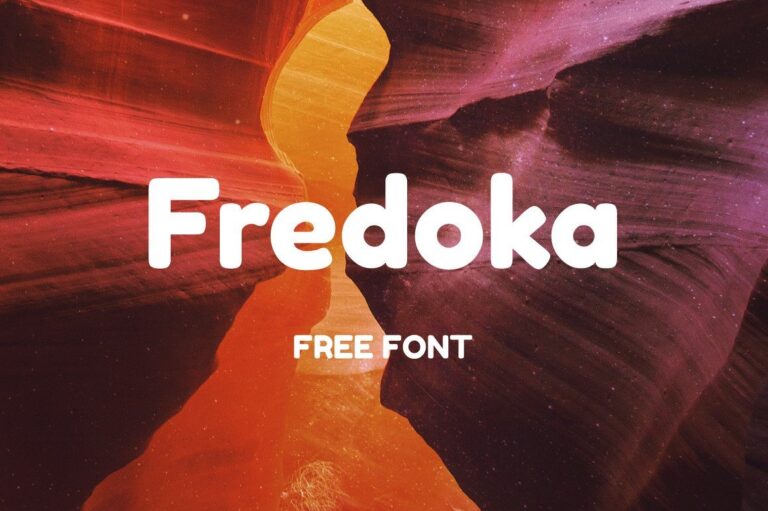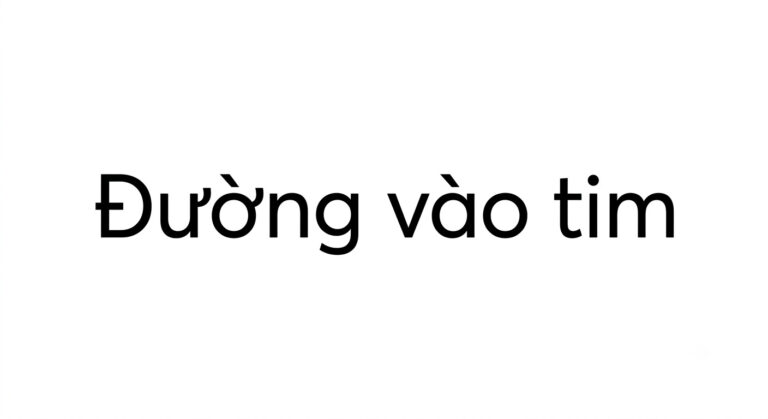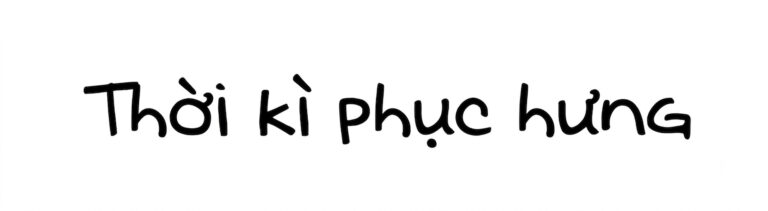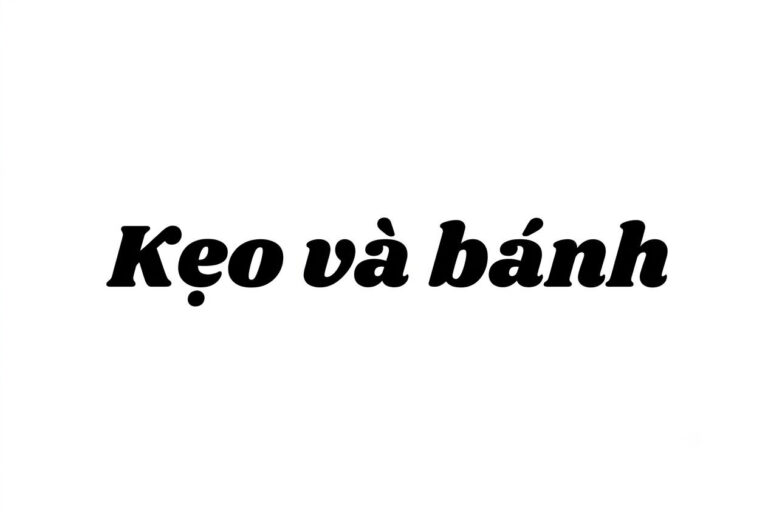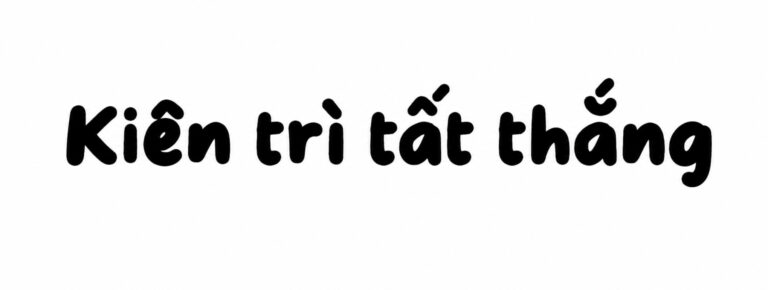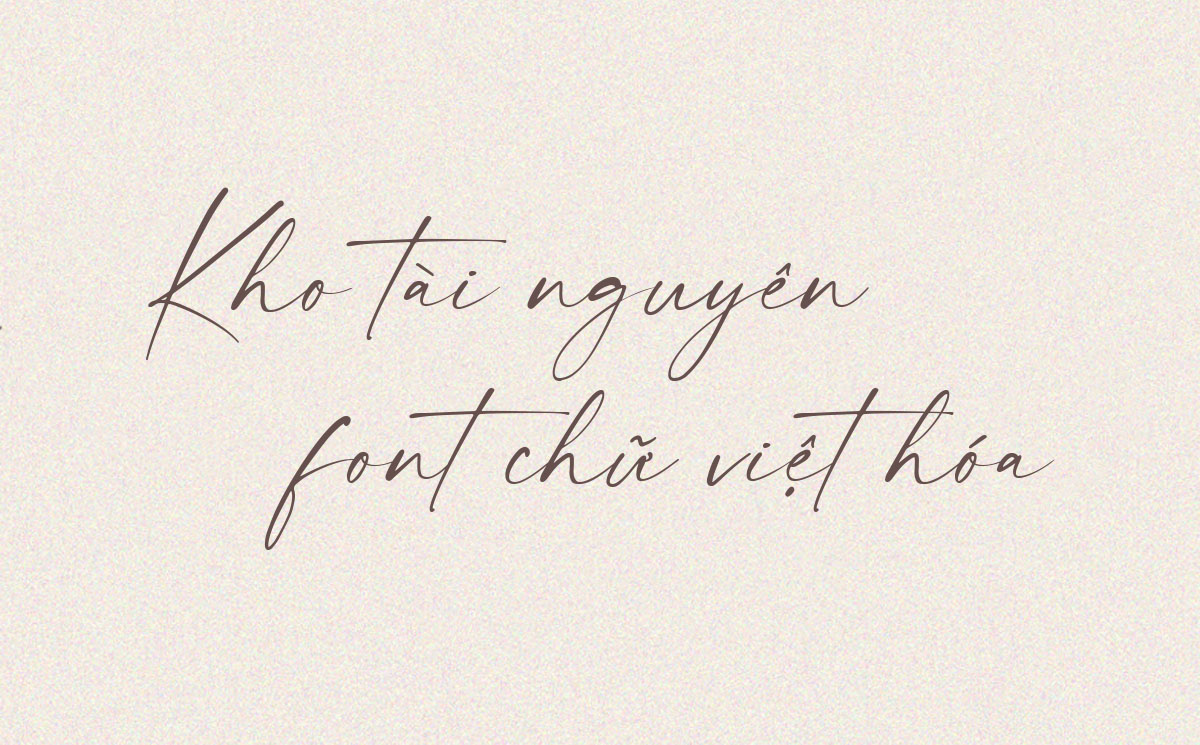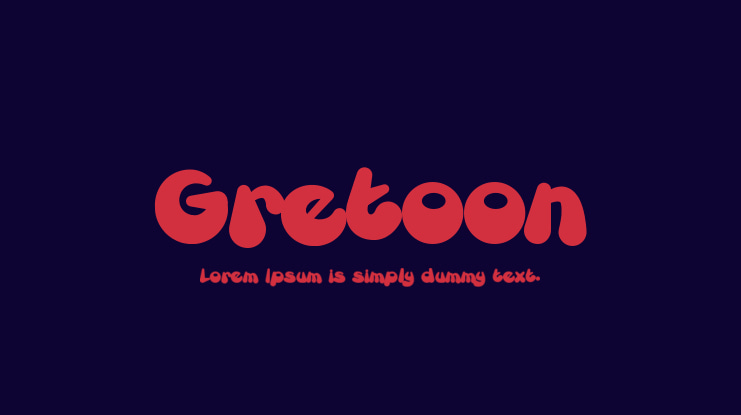
Tải 10+ bộ Font Handwriting Việt hóa sắc nét chuyên cho thiết kế bao bì
Nhiều designer gặp khó khăn khi tìm kiếm Font Handwriting Việt hóa do một số bộ font chưa được xử lý đầy đủ ký tự tiếng Việt, dẫn đến lỗi mất dấu, sai ký tự hoặc nét chữ bị răng cưa khi đưa vào sản xuất. Những vấn đề này khiến các mẫu bao bì thủ công mất đi vẻ tự nhiên, giảm cảm giác gần gũi và tính cá nhân hóa của thương hiệu.
Xưởng In Viva cung cấp Font Handwriting Việt hóa với hệ thống ký tự chuẩn nét, hỗ trợ hiệu quả trong quá trình thiết kế logo, bao bì giấy và sản xuất các dòng quà tặng doanh nghiệp theo phong cách thủ công, sáng tạo.
Handwriting font chữ viết tay là gì?
Handwriting font chữ viết tay là tập hợp những phông chữ được thiết kế mô phỏng lại các đường nét viết tay thực tế của con người. Thay vì tuân theo những tỷ lệ hình học cứng nhắc như dòng chữ Sans-serif hay Serif, phông chữ Handwriting mang đặc trưng của sự tự do, phóng khoáng và đôi khi là sự không đồng đều có chủ ý. Tùy thuộc vào công cụ mô phỏng (bút chì, bút mực, cọ lông hay phấn), dòng phông chữ này có thể mang lại những sắc thái cảm xúc khác nhau: từ lãng mạn, nhẹ nhàng đến cá tính, bụi bặm.
Trong ngành thiết kế đồ họa và bao bì, phông chữ viết tay đóng vai trò như một cầu nối cảm xúc, giúp sản phẩm trở nên thân thiện và mang đậm dấu ấn cá nhân hơn. Tuy nhiên, bản gốc của các phông chữ này thường là tiếng Anh, khi áp dụng vào ngôn ngữ có nhiều dấu thanh như tiếng Việt rất dễ xảy ra tình trạng lỗi font, sai khoảng cách hoặc các dấu bị đè lên nhau. Bộ Font Handwriting Việt hóa do In Viva tổng hợp đã được căn chỉnh kỹ thuật tỉ mỉ, giúp các dấu tiếng Việt hòa hợp tự nhiên với nét bút gốc, mang lại sự thuận tiện cho người sử dụng.
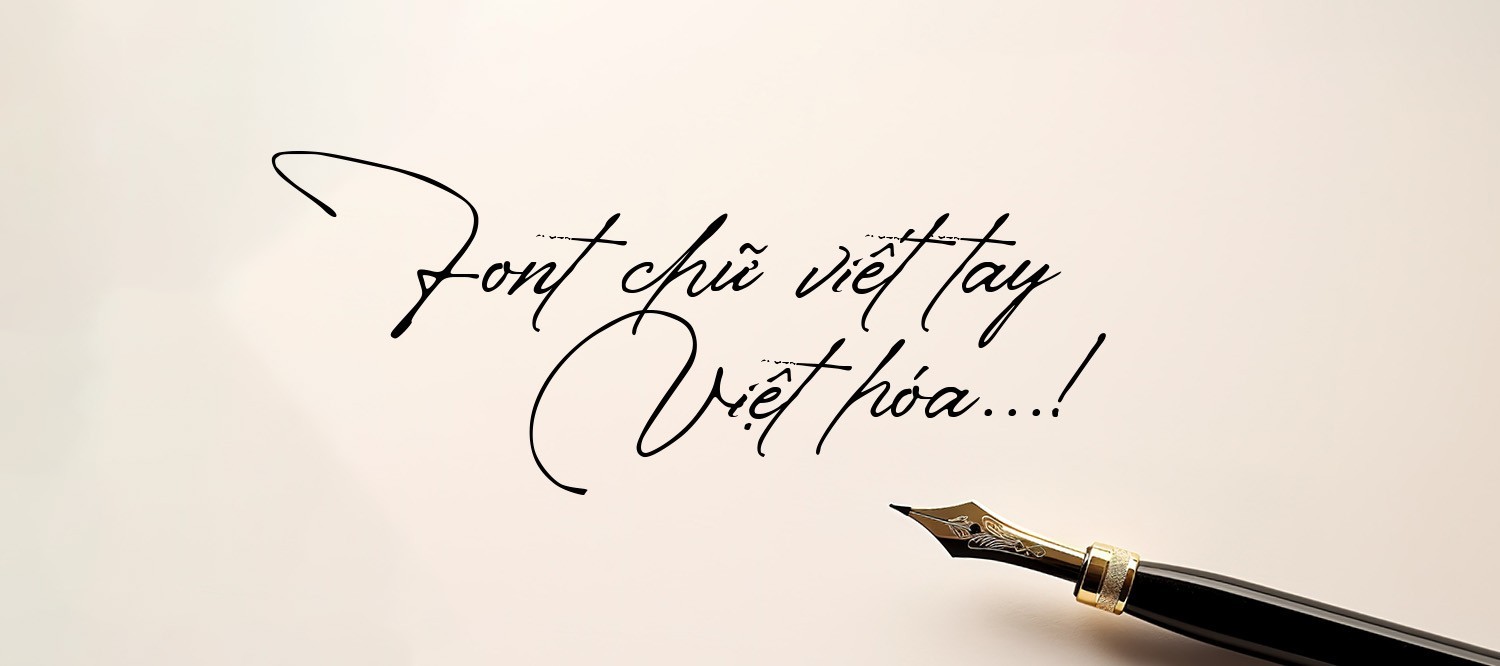
Handwriting Font đẹp 01
Lưu ý: Khi thiết kế với Handwriting font chữ viết tay, bạn nên kết hợp sử dụng trên nền giấy có độ nhám như giấy Kraft hoặc giấy mỹ thuật có vân. Điều này sẽ giúp tăng hiệu ứng thị giác, khiến nét chữ trông chân thực như được viết bằng tay trực tiếp lên sản phẩm.
5 ứng dụng Handwriting Font Việt hóa trong thiết kế và in ấn
Nhờ phong cách chữ viết tay tự nhiên, mềm mại cùng khả năng truyền tải cảm xúc tốt, Handwriting Font Việt hóa được ứng dụng linh hoạt trên nhiều sản phẩm bao bì, quà tặng và ấn phẩm thương hiệu theo hướng gần gũi, sáng tạo:
• Thiết kế bao bì sản phẩm Organic và Handmade: Font Handwriting phù hợp để thể hiện tên thương hiệu, thông điệp sản phẩm trên hộp giấy, tem nhãn hoặc túi giấy. Nét chữ tự nhiên giúp các dòng sản phẩm như xà phòng thiên nhiên, trà thảo mộc, nến thơm tạo cảm giác mộc mạc và đáng tin cậy.
• Sản xuất thiệp cảm ơn và ấn phẩm tri ân khách hàng: Những lời nhắn gửi, câu chúc hoặc thông điệp cảm ơn sử dụng Font Handwriting giúp doanh nghiệp tạo cảm giác chân thành, tăng sự kết nối với khách hàng thông qua Thank You Card, voucher hoặc thiệp đính kèm sản phẩm.
• In ấn bao bì ngành F&B: Font Handwriting có thể ứng dụng trên ly giấy, túi giấy đựng bánh, hộp cafe hoặc bao bì thực phẩm. Kiểu chữ mềm mại giúp thương hiệu truyền tải phong cách thân thiện, trẻ trung và phù hợp với các sản phẩm thủ công.
• Thiết kế túi vải Canvas và sản phẩm thời trang: Các câu quote, slogan hoặc logo sử dụng font chữ viết tay khi in trên túi Tote, áo thun hoặc phụ kiện giúp sản phẩm thể hiện cá tính riêng, phù hợp với phong cách sống hiện đại.
• Khắc laser quà tặng cá nhân hóa: Font Handwriting phù hợp để khắc tên riêng, lời chúc hoặc chữ ký lên sổ tay bìa da, hộp gỗ, bút ký và bình giữ nhiệt. Các đường nét mô phỏng chữ viết tay giúp món quà trở nên tinh tế và mang dấu ấn cá nhân hơn.
Handwriting Font đẹp 02
5 lưu ý khi sử dụng Handwriting Font Việt hóa
Để Font Handwriting Việt hóa giữ được vẻ đẹp tự nhiên và đảm bảo độ sắc nét khi sản xuất thực tế, designer cần chú ý:
• Kiểm soát độ dày nét chữ khi in: Các font viết tay thường có nhiều nét thanh mảnh. Khi in trên giấy Kraft, giấy mỹ thuật hoặc chất liệu hút mực, nên kiểm tra kích thước chữ để hạn chế tình trạng mất nét hoặc chữ bị nhòe.
Có, đội ngũ thiết kế của In Viva hỗ trợ tư vấn bố cục, lựa chọn font chữ và phương án gia công phù hợp khi khách hàng đặt sản xuất trực tiếp tại xưởng.